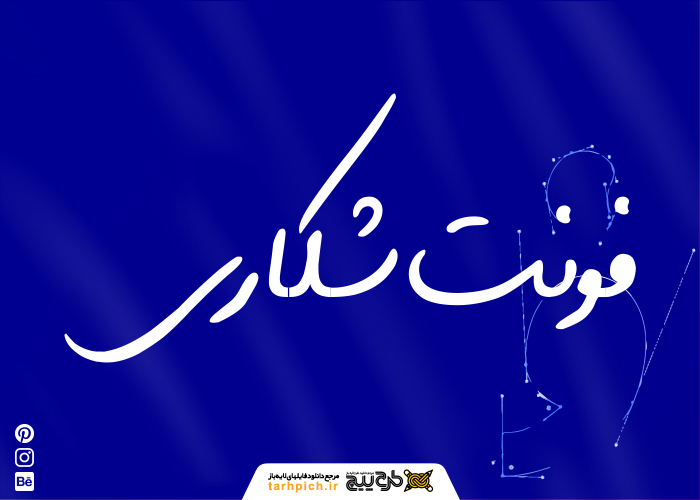
فونت شکاری
در فونت فارسی  شکاری از فرمت  TTF -eot-WOFFاستفاده شده است.حالت این فونت معاصر و مدرن است.فونت شکاری از مجموعه فونت های آزاد و دست نویس است و یک وزن معمولی دارد.این نوع فونت از نظر نوشتاری خیلی زیبا است و قابل استفاده در تمامی نرم افزار ها است .اگر به دنبال سایت گرافیک برای فونت های خود هستید روی لینک کلیک کنید.